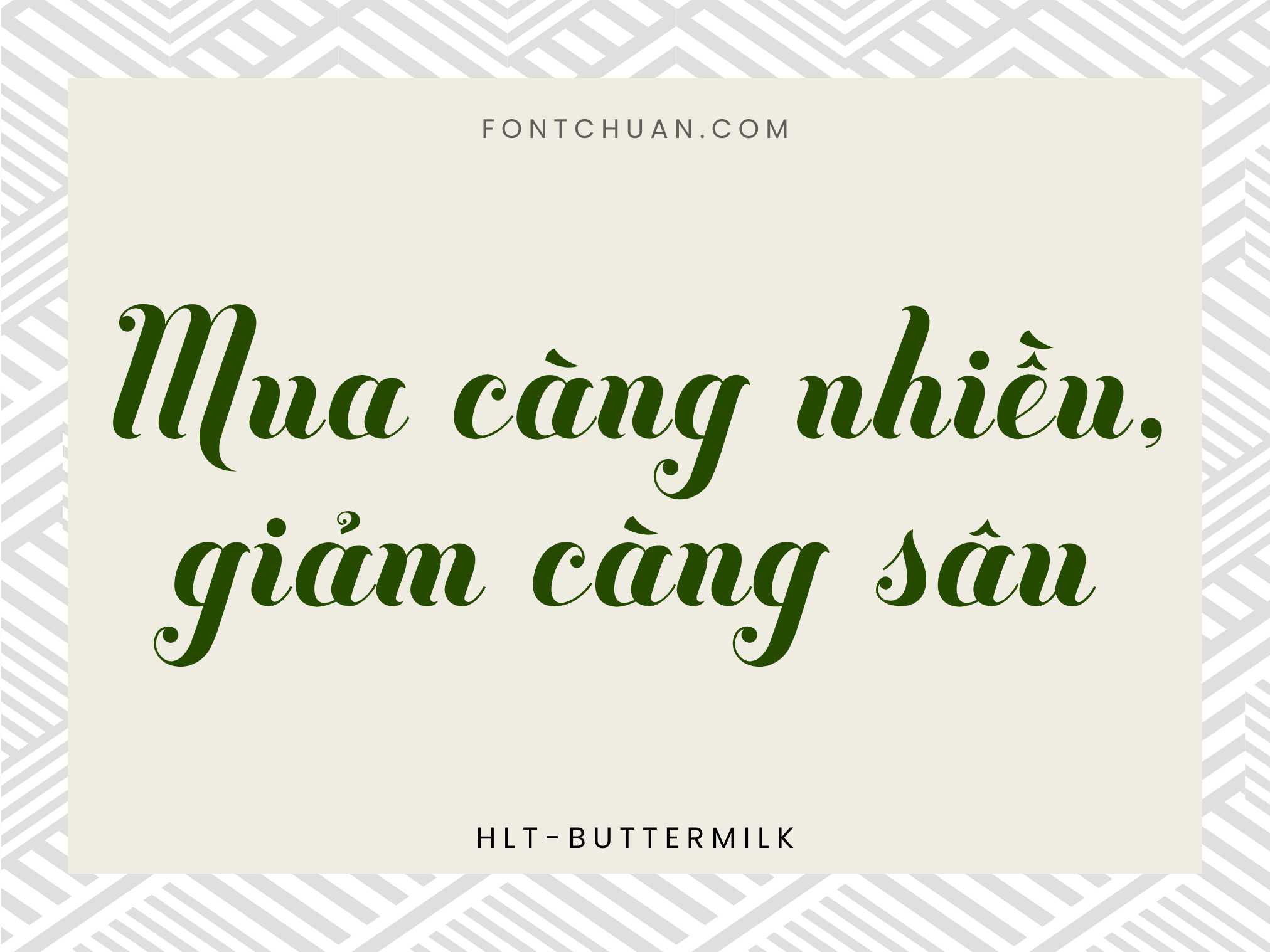
Font HLT Buttermilk Việt Hóa
Việt hóa bởi: Hlt
Buttermilk là một phông chữ viết tay thanh lịch, được thiết kế bởi Jessica Hische vào năm 2008. Phông chữ này mang đến cảm giác mượt mà và tinh tế, với các đường nét uyển chuyển và duyên dáng, phù hợp cho nhiều dự án thiết kế khác nhau. Với sự Việt hóa của HLT, Buttermilk hỗ trợ đầy đủ các ký tự tiếng Việt, giúp người dùng dễ dàng áp dụng trong các thiết kế đa ngôn ngữ. Thành viên của Font Chuẩn đã sưu tầm và chia sẻ phông chữ này nhằm đáp ứng nhu cầu đa dạng của cộng đồng thiết kế.
Về đặc điểm thiết kế, Buttermilk sở hữu các ký tự mềm mại với những nét cong tinh tế, tạo nên sự ấm áp và thân thiện. Phông chữ này đặc biệt phù hợp cho các dự án như thiệp mời, bìa sách, poster, logo và các ấn phẩm quảng cáo, nơi cần sự cuốn hút và độc đáo. Ngoài ra, Buttermilk cũng thích hợp cho các sự kiện như lễ hội, sinh nhật, Valentine và Trung thu, mang lại không khí vui tươi và lãng mạn. Trong lĩnh vực ngành nghề, phông chữ này được ứng dụng rộng rãi trong quảng cáo, thiết kế thiệp cưới, giáo dục và công nghệ, góp phần tạo nên sự chuyên nghiệp và ấn tượng cho các sản phẩm và thương hiệu.